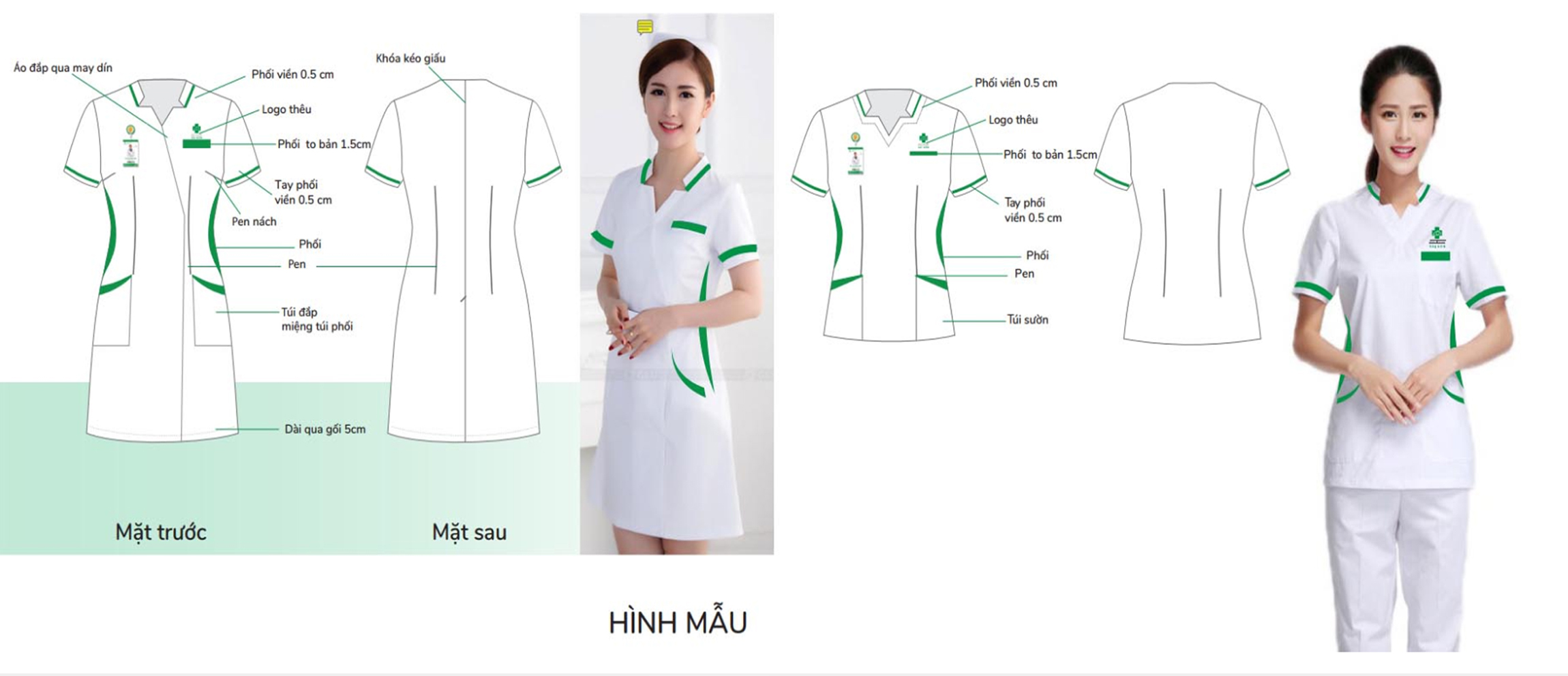
Một chi tiết nhỏ có thể làm lu mờ giá trị của hàng chục năm học tập. Trên nền áo blouse trắng, chuỗi ký tự “PGS.TS.BS.CKII” dài có thể trông rối mắt nếu không được xử lý đúng kỹ thuật. Đối với các đơn vị y tế, thêu áo blouse không chỉ là vấn đề thẩm mỹ mà còn thể hiện sự tôn trọng đối với chuyên môn của nhân sự. Bài viết này cung cấp hướng dẫn kỹ thuật cho các nhà quản lý, giúp xác định cách thể hiện chức danh y tế một cách chuẩn xác và chuyên nghiệp.
Font chữ thêu: Vì sao in đậm thường an toàn hơn chữ nghiêng?
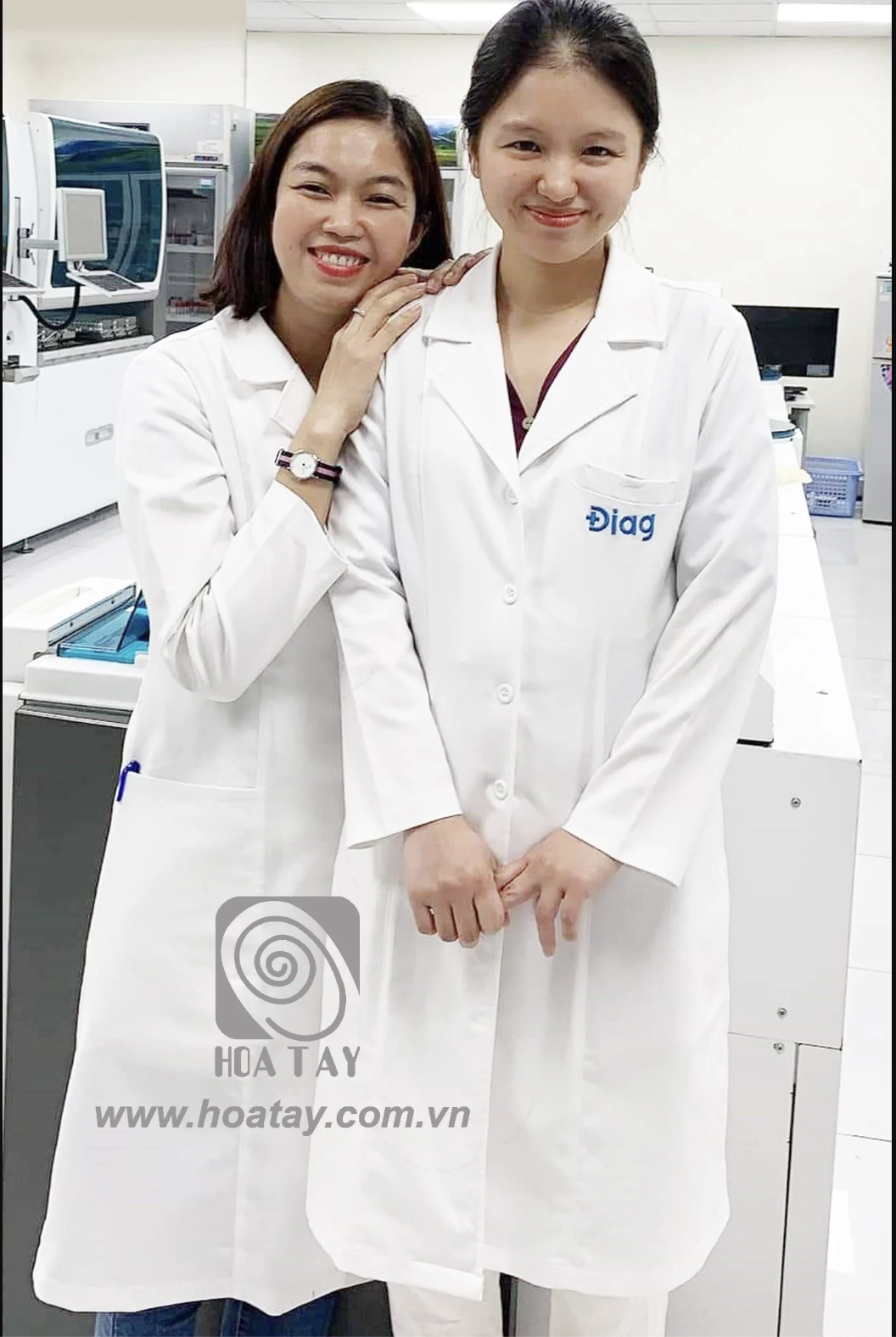
Khi xử lý một chuỗi ký tự dài như PGS.TS.BS.CKII, tính dễ đọc là ưu tiên hàng đầu. Font chữ thêu dạng in đậm (bold) tạo nên các đường nét vững chãi, đảm bảo nội dung rõ ràng khi nhìn từ xa. Điều này rất quan trọng với các chức danh y tế cao cấp, nơi mỗi chữ cái cần được nhận diện chính xác và trang trọng. Ngược lại, font chữ nghiêng (italic) hoặc kiểu viết tay (cursive) tiềm ẩn rủi ro lớn ở kích thước thêu nhỏ, chỉ khoảng 4mm. Ở tỷ lệ này, những nét cong dễ bị nhòe hoặc dính vào nhau, làm mất đi sự chỉn chu mà nhà quản lý hình ảnh luôn hướng tới.
Bản vẽ kỹ thuật đồng phục cho thấy sự chính xác cần thiết trong từng chi tiết, từ phôi viền đến vị trí logo.
Nhóm font phù hợp với áo blouse
Trong môi trường y tế, sự cân bằng giữa thẩm mỹ và công năng là then chốt. Nhóm font không chân (sans-serif) như Arial hoặc Tahoma thường được khuyến nghị do cấu trúc đơn giản, ít chi tiết thừa. Loại font này giúp máy thêu xử lý các góc cạnh của chữ sắc nét, tránh hiện tượng búi chỉ ở các chữ cái phức tạp như G hay S. Nếu cơ sở y tế ưu tiên vẻ truyền thống, nhóm font có chân (serif) như Times New Roman vẫn là lựa chọn an toàn, provided rằng kích thước thêu đủ lớn để các nét chân không bị lẫn vào nhau.
Cân đối theo độ dài tên
Quy tắc chung trong thêu áo blouse là: chuỗi ký tự càng dài, font càng cần sự ổn định. Với tên dài kèm chức danh, việc sử dụng font sans-serif in đậm giúp kiểm soát không gian, giữ cho dòng chữ gọn gàng và dễ đọc. Trong khi đó, nếu chỉ thêu tên ngắn hoặc một chức danh đơn, bạn có thể linh hoạt hơn, thậm chí cân nhắc các font có nét thiết kế nhẹ nhàng để tạo điểm nhấn cá nhân mà vẫn giữ được nét chuyên nghiệp. Chúng ta nên xem xét tổng thể độ dài ký tự trước khi chọn font để đảm bảo dòng chữ không bị vượt quá vùng ngực trái quy định, tránh gây mất cân đối trên trang phục. Nếu chuỗi thêu tên vượt quá 15 ký tự, việc chia dòng hoặc rút gọn chức danh là giải pháp tối ưu để duy trì thẩm mỹ. Một dòng chữ thêu tên được cân đối sẽ là điểm nhấn tinh tế, tôn lên vẻ trang trọng của bộ đồng phục y tế.
Quy tắc chuẩn về khoảng cách và thứ tự
Khi thực hiện thêu áo blouse, việc bố trí đúng vị trí là yếu tố then chốt để tránh chồng lấp giữa logo bệnh viện, chức danh và bảng tên. Nguyên tắc chung quy định logo phải nằm ở vùng cao nhất của ngực trái. Ngay bên dưới logo, cách khoảng 2 đến 3 cm, là dòng chữ chứa họ tên và chức danh. Khoảng cách này đảm bảo tầm nhìn rõ ràng cho người đối diện mà không tạo cảm giác chật chội hay rối mắt trên nền vải trắng.
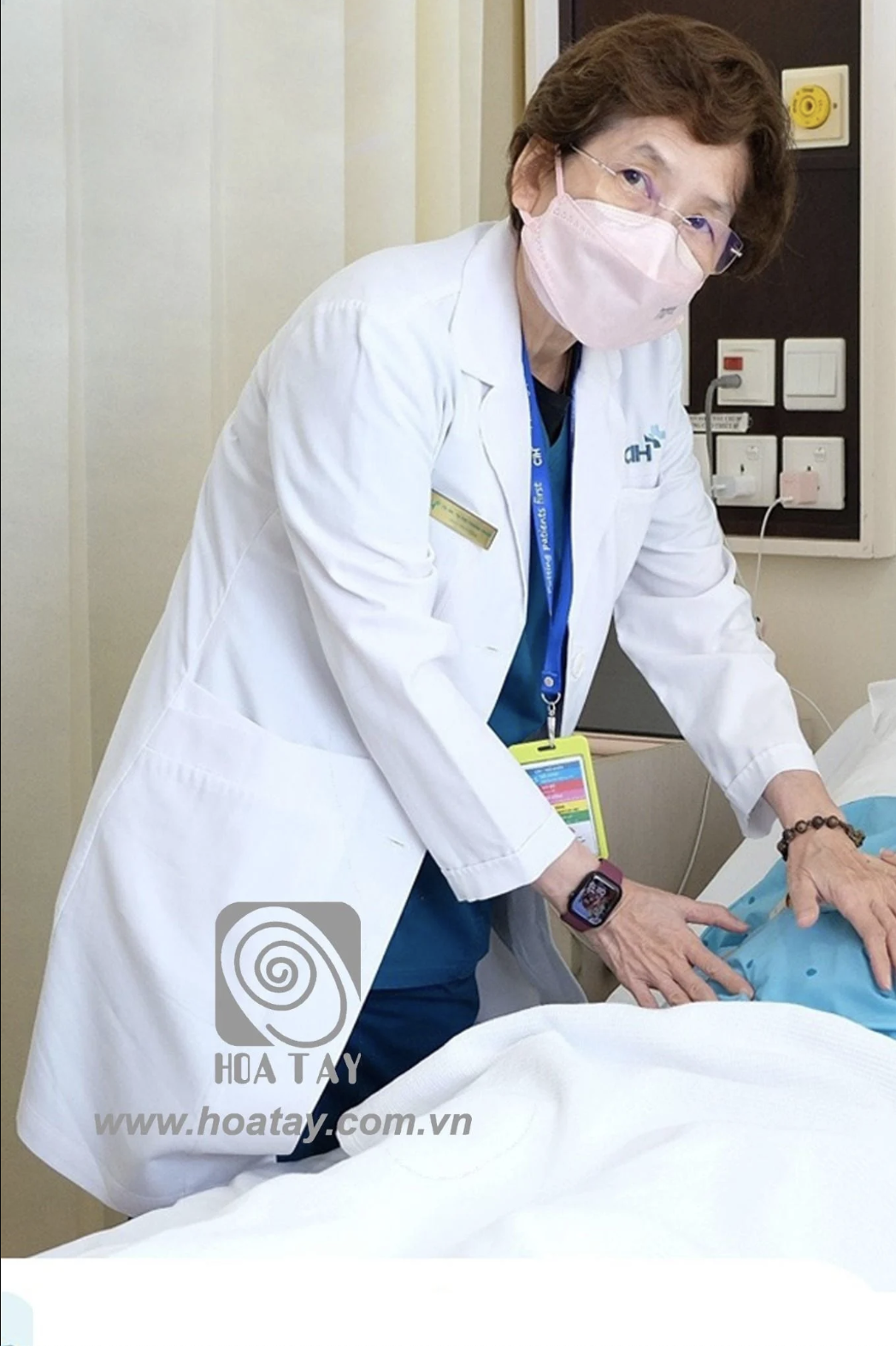
Nếu tổ chức của bạn yêu cầu độ chính xác cao trong đồng phục, hãy đối chiếu với bản vẽ kỹ thuật. Một tiêu chuẩn phổ biến trong ngành đặt logo ở vị trí cách mép vai 8–10 cm.
Dòng tên và chức danh sẽ xếp ngay ngắn theo trục dọc, đảm bảo tính thẩm mỹ và sự tôn trọng đối với vị thế của nhân viên y tế.
Nguyên tắc 15 ký tự và phân biệt bảng tên
Ngành đồng phục y tế có một quy tắc thẩm mỹ không viết thành văn bản nhưng được áp dụng rộng rãi: chuỗi ký tự (tên + chức danh) nên giới hạn dưới 15 ký tự. Nếu chuỗi thông tin quá dài, ví dụ “PGS.TS.BS.CKII” kết hợp với họ tên dài, cần chia thành hai dòng hoặc lược bớt các cấp bậc nhỏ hơn để giữ được sự cân đối trên mặt áo.
Cần phân biệt rõ giữa thêu tên và bảng tên. Thêu tên là giải pháp cố định, mang tính thẩm mỹ và thể hiện sự thuộc về tổ chức lâu dài. Trong khi đó, bảng tên là phụ kiện tháo lắp, phục vụ mục đích xác thực chức danh và tên tuổi trong từng thời điểm. Khi xác định vị trí thêu, tuyệt đối không để mũi kim thêu lấn vào khu vực mà bảng tên thường được kẹp, tránh gây khó chịu hoặc hư hỏng áo sau nhiều lần sử dụng.
Chỉ thêu và độ bền: Cotton hay Polyester trên nền vải trắng?
Trên nền vải trắng của blouse, việc lựa chọn chất liệu chỉ quyết định trực tiếp đến độ sắc nét của chữ thêu theo thời gian. Trong khi chỉ cotton có ưu điểm về sự tự nhiên và mềm mại, nó lại dễ bị phai màu và mất độ bóng sau nhiều lần giặt công nghiệp.
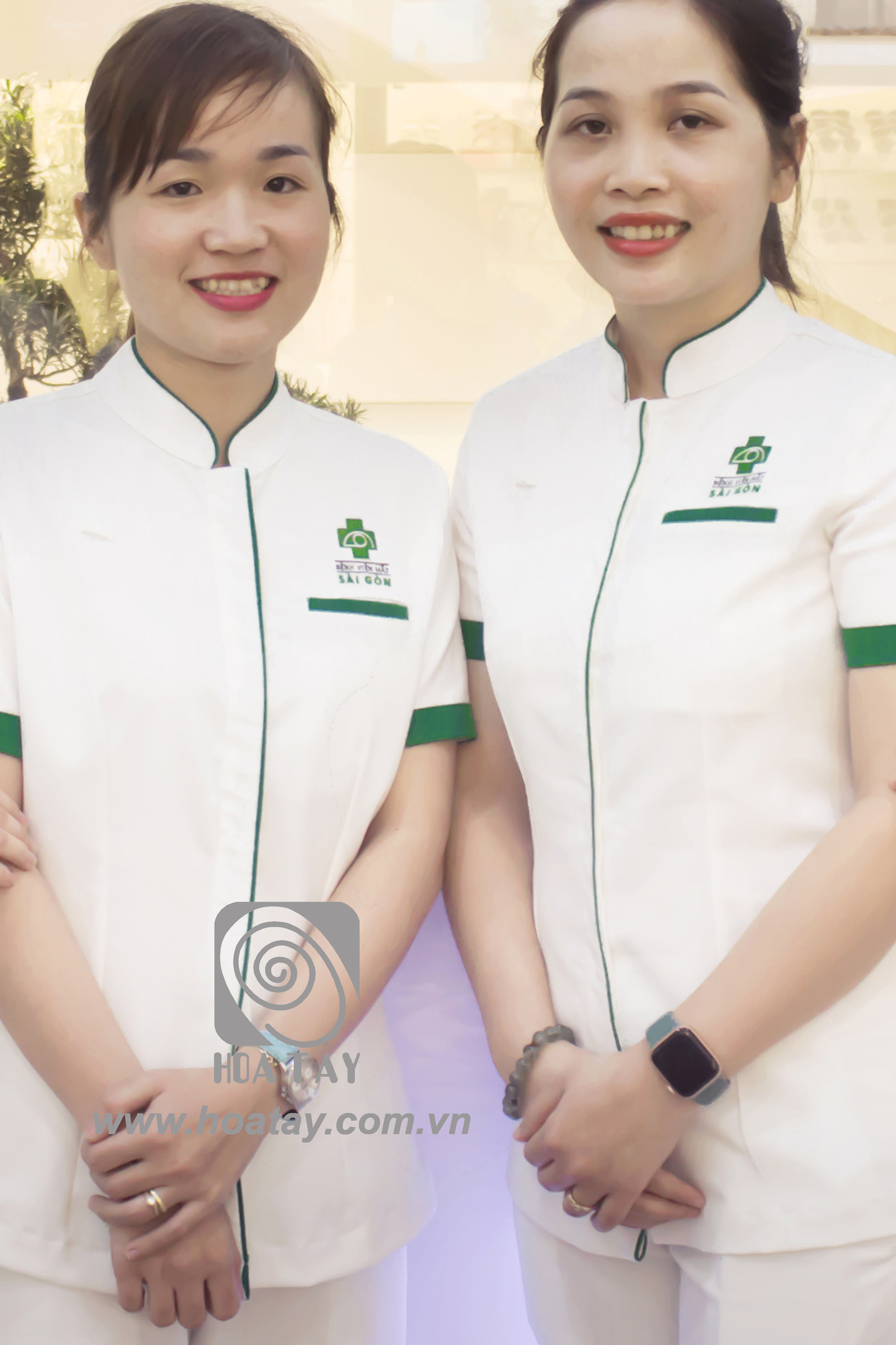
Ngược lại, chỉ polyester cao cấp giữ được độ bóng và khả năng bám màu vượt trội, giúp duy trì vẻ trang trọng cần thiết cho các chức danh y tế cao. Sự khác biệt này trở nên rõ rệt khi áo trải qua quy trình tẩy trùng thường xuyên tại bệnh viện. Để đảm bảo tính thẩm mỹ, nên ưu tiên các tông màu có độ tương phản cao như xanh đậm, đen hoặc màu đặc trưng của đơn vị. Các tông màu nhạt dễ gây khó đọc và làm giảm tính chuyên nghiệp của bộ đồng phục.